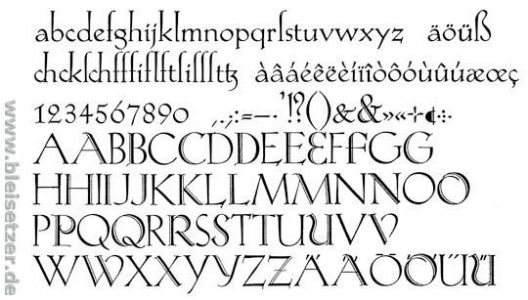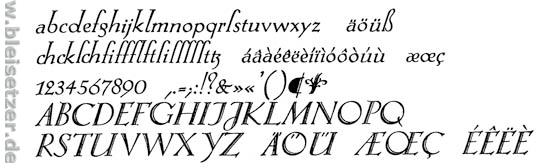
Meine Einzigartigkeit ist meine Schönheit
die Kontaktgruppe "Strohhalm" für Betroffene von Ess-Störungen bei uns am Gesundheitsamt macht heuer eine öffentliche Veranstaltung mit dem Thema "Meine Einzigartigkeit ist meine Schönheit". Dazu soll ein Banner erstellt werden (ca. 250 cm breit) mit dem Motiv, das hier zu sehen ist (also keine Dünenlandschaft, sondern ein Tuch). Der Text unten links und rechts ist festgelegt, ich hoffe aber, man kann dort mit der Schrift noch etwas machen (links Frutiger, rechts Helvetica Condensed Bold). Gesucht ist nun eine passende Schrift für den Text, der das Banner zieren soll, eben das genannte Thema "Meine Einzigartigkeit ist meine Schönheit".
Hat jemand Vorschläge?
Vielleicht eine freundliche Slab-Serif – PMN Caecilia (etwas ernster) oder Chaparral (menschelt mehr).
Oder die Dolly von underware, um eine lebendige Antiqua zu nennen.
Guten Tag Dieter
Ich könnte mir zu diesem sensiblen Thema eine gut lesbare, persönliche Handschrift* vorstellen – das würde auch die Aussage "Meine Einzigartigkeit ..." optisch unterstützen.
* Wie wärs mit deiner eigenen? Sie hat was feines, weiches, vielleicht verletzliches (wenn ich mir diese Bemerkung erlauben darf, sonst lösch' ich das sofort wieder). Probier das doch mal ...
Meine Meinung:
"Meine Einzigartigkeit ist meine Schönheit"
Diese Aussage ist nicht steigerungsfähig.
Ich empfinde ihn als wunderschön gewählt in Bezug auf das Thema.
Denn er bringt das Problem haargenau auf den Punkt.
Ich meine, man sollte eine Schrift wählen, die ohne jeden Zweifel genau diesem Anspruch entspricht. Und dies durch ihre Anmutung sowohl dem Laien als auch dem Fachkundigen vermittelt.
Rudolf Koch
Koch-Antiqua oder Koch-Kursiv.
Das wäre meine Wahl.
Vielleicht eine freundliche Slab-Serif – PMN Caecilia (etwas ernster)
Hm, ich weiß nicht. Ist die vielleicht nicht etwas arg dünn? ... Ach Blödsinn, es gibt ja nicht nur den Light-Schnitt ... Hm, ich weiß trotzdem noch nicht. Slab Serif, in diese Richtung hätte ich dabei überhaupt nicht gedacht. Ich werd's mal über Nacht wirken lassen.
oder Chaparral (menschelt mehr).
Ja, ein bißchen. Es ist im Großen und Ganzen dieselbe Richtung wie die Caecilia.
Oder die Dolly von underware, um eine lebendige Antiqua zu nennen.
Die kommt bei den Kolleginnen sicher besser an.
[...] eine gut lesbare, persönliche Handschrift [...]Wie wärs mit deiner eigenen? Sie hat was feines, weiches, vielleicht verletzliches (wenn ich mir diese Bemerkung erlauben darf, sonst lösch' ich das sofort wieder). Probier das doch mal ...
Natürlich darfst Du das sagen, und ich finde das höchst interessant. Mir selber kommt meine Handschrift eher unordentlich, zerstückelt, ohne Schwung und Linie vor.
Ein Graphologe würde vielleicht sagen können, daß die Schrift nicht von einer Frau ist, und fast alle Leute, die bei uns wegen Ess-Störungen kommen, sind Frauen. Da könnte vielleicht besser eine Kollegin ihre Handschrift zur Verfügung stellen.
Wie sieht das denn mit der Qualität aus? Das Banner ist 250 cm breit, würde ein meinetwegen mit 1200 dpi eingescannter Schriftzug in der entsprechenden Vergrößerung noch reichen, damit's nicht zu verpixelt aussieht? Mit so großen Formaten habe ich keine Erfahrung.
Koch-Antiqua oder Koch-Kursiv.
Das wäre meine Wahl
Danke, Georg. Aber das angesprochene Klientel ist sehr problembehaftet. So schön die beiden Koch-Schriften sind, ich empfinde sie für diesen Zweck als zu kunstvoll.
[…] eher unordentlich, zerstückelt, ohne Schwung und Linie vor. […]
Das hätte ich so nie zu formulieren gewagt :oops: . Aber präzis diese Schriftstimmung wollte ich ansprechen. Hinsichtlich der "Zielgruppe" (man muss sich ja fast schämen!) sehe ich gerade diese Qualitäten als sehr treffend. Und zum feinen Tuch tät's auch noch passen. Würde dir jetzt sehr gerne sofort ein kleines Muster machen. Aber leider geht mein Zug demnächst und meine Handschrift ist sowieso total unpassend …
Ein Graphologe würde vielleicht sagen können, daß die Schrift nicht von einer Frau ist, und fast alle Leute, die bei uns wegen Ess-Störungen kommen, sind Frauen. Da könnte vielleicht besser eine Kollegin ihre Handschrift zur Verfügung stellen.
Meines Erachtens hier unerheblich, was der Herr Graphologe sagen können könnte. Es geht bloß darum, Betroffene in einem sehr flüchtigen Augenblick visuell abzuholen (Banner). Wie auch immer: die Idee, deine Kolleginnen schreiben zu lassen, find' ich sicher einen Versuch wert.
Wie sieht das denn mit der Qualität aus? Das Banner ist 250 cm breit, würde ein meinetwegen mit 1200 dpi eingescannter Schriftzug in der entsprechenden Vergrößerung noch reichen, damit's nicht zu verpixelt aussieht? Mit so großen Formaten habe ich keine Erfahrung.
Das dürfte kein Problem sein. Erkundige dich aber besser bei deinem Servicebüro betreffs Printerauflösung. Weitere Möglichkeit: Handschrift im Illustrator vektorisieren. Auf die große Betrachterdistanz wären die resultierenden Vektorunschönheiten wohl marginal.
Erst motzen und sich dann nicht wieder melden. Typisch, nicht. Entschuldige also meine unanständig lange Warterei.
Vielen Dank für den Kommentar. Und: Nein, da gibt's nichts zu entschuldigen, weil's ja auch keinen Anspruch gibt, daß Du etwas dazu schreibst. Für mich ist das ok, mir geht's auch manchmal so.